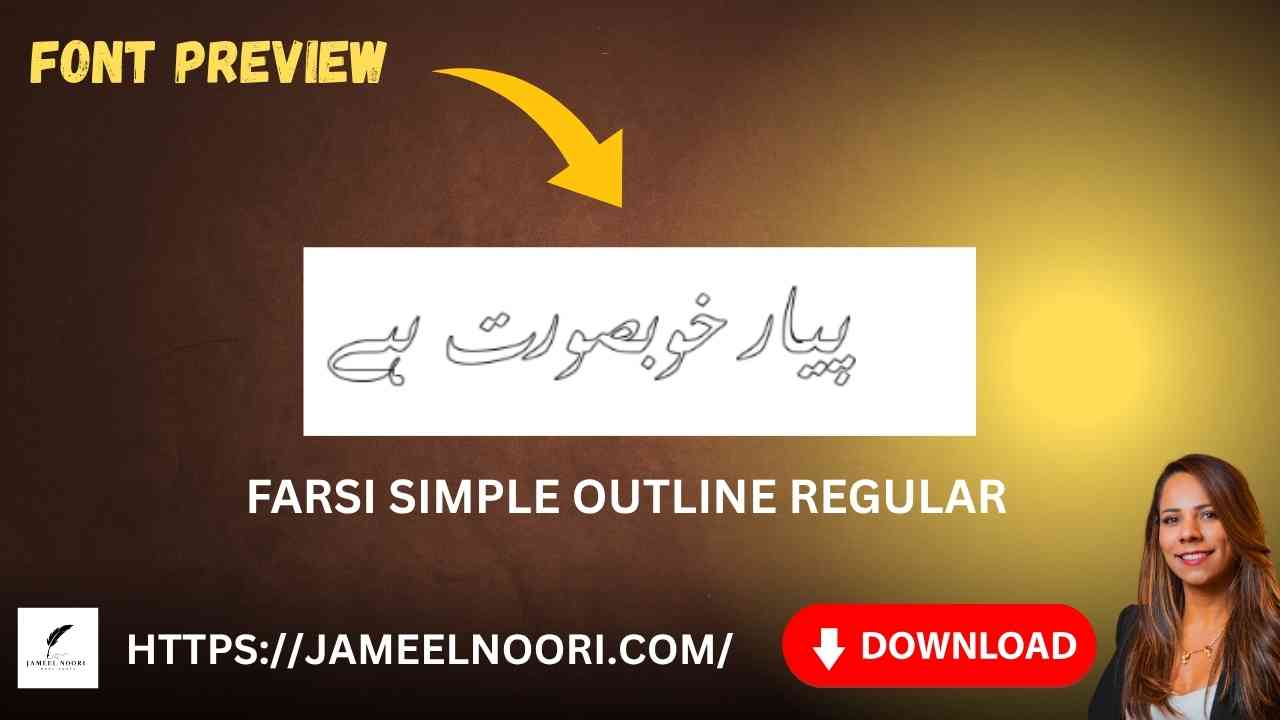
Agar aap stylish aur modern Urdu likhne ke liye ek unique font dhoond rahe hain, to Download Urdu font Farsi Simple Outline Regular aap ke liye best choice ho sakta hai. Ye font na sirf visually appealing hai balki readability bhi improve karta hai, khas kar design aur calligraphy projects ke liye.
What is Farsi Simple Outline Regular Font?
Download Urdu font Farsi Simple Outline Regular ek TrueType font (TTF) hai jo ke outline style me banaya gaya hai. Is font ka design lightweight aur stylish hai, jise aap headings, posters, banners aur creative Urdu content me use kar sakte hain.
- Font Name: Farsi Simple Outline Regular
Features of Download Urdu font Farsi Simple Outline Regular
Yeh font kai khaas features offer karta hai jo ise dusre Urdu fonts se alag banata hai:
Main Features:
- Stylish outline design
- Clear readability on screen & print
Use Cases – Farsi Simple Outline Regular Font Ka Istemaal Kahan Hota Hai?
Aap is font ka use kai jagahon pe kar sakte hain:
Benefits of Using Farsi Simple Outline Regular in Pakistan
Pakistan ke kai cities jaise Lahore, Karachi, Islamabad me designers is font ka use kar rahe hain because:
- Modern look provide karta hai
- Achi visual appearance deta hai especially screen pe
Tips for Better Usage of Farsi Simple Outline Regular
- Bold headings ke liye is font ko use karein
- Calligraphy-style designs me perfect results deta hai
Agar aap apne Urdu writing style ko upgrade karna chahte hain, to Download Urdu font Farsi Simple Outline Regular zarur try karein. Iska outline design modern hai, readability excellent hai, aur compatibility har platform ke sath perfect hai. Yeh font har designer, blogger, ya Urdu content writer ke liye ek “Expert Choice” hai.
FAQs – Download Urdu font Farsi Simple Outline Regular
What type of font is Farsi Simple Outline Regular?
It is a TrueType Urdu font with an outlined visual style suitable for headings and design.
Is this font suitable for professional printing?
Yes, its outline style gives a clean and modern look in both digital and print formats.